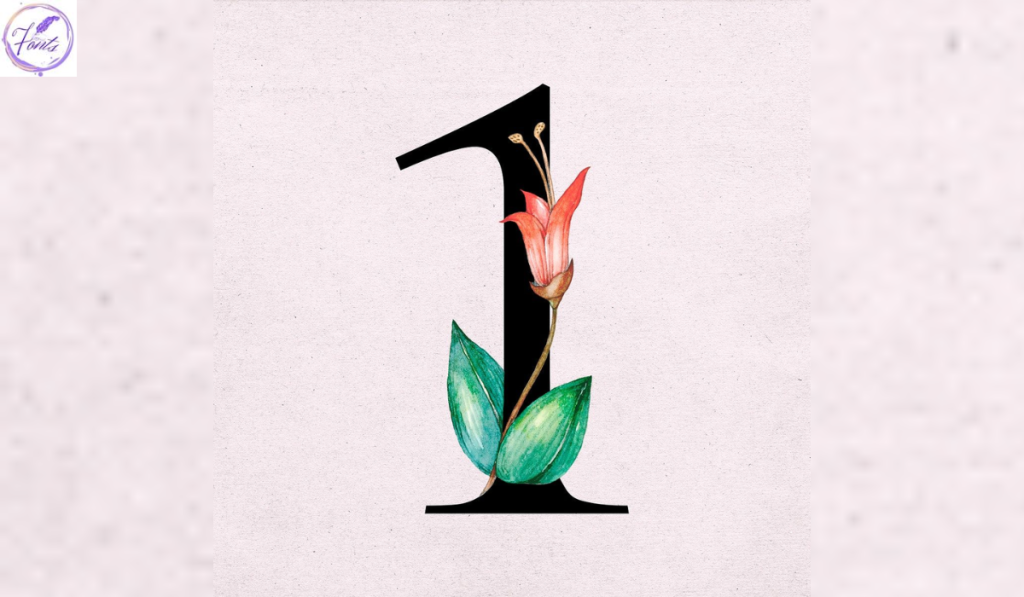
Font One Typography việt hóa
Tác giả: Jane Smith
Ngày phát hành: 2020
Ngôn ngữ: Tiếng Việt, Tiếng Anh, và nhiều ngôn ngữ khác
Bộ Font: Type-One
Phân loại: Cá tính, độc đáo
Kiểu chữ: Kiểu chữ đa dạng
Font one typography là một kiểu chữ hiện đại và độc đáo, được thiết kế để mang lại sự mới mẻ và sáng tạo cho các dự án thiết kế. Ra mắt vào năm 2020 bởi nhà thiết kế nổi tiếng Jane Smith, font này nhanh chóng trở nên phổ biến nhờ vào kiểu dáng thanh lịch và dễ đọc. Với các đường nét tinh tế và tỉ mỉ, font one typography không chỉ phù hợp cho các dự án kỹ thuật số mà còn cho các ấn phẩm in ấn. Đặc biệt, font này đã được Việt hóa hoàn toàn, giúp bạn dễ dàng sử dụng trong các dự án tiếng Việt mà không gặp phải bất kỳ trở ngại nào về ký tự.
Đánh giá font one typography
Font one typography nhận được rất nhiều lời khen ngợi từ cộng đồng thiết kế nhờ vào tính ứng dụng cao và vẻ đẹp thẩm mỹ của nó. Nhiều nhà thiết kế đã sử dụng font này cho các dự án của mình và đánh giá cao sự linh hoạt và dễ đọc của nó. Tạp chí thiết kế uy tín “Design World” đã xếp hạng font one typography là một trong những font chữ đẹp và sáng tạo nhất của năm 2020. Với khả năng hiển thị rõ ràng trên cả màn hình và bản in, font này chắc chắn sẽ là lựa chọn lý tưởng cho các thiết kế từ logo, poster đến các tài liệu quảng cáo.